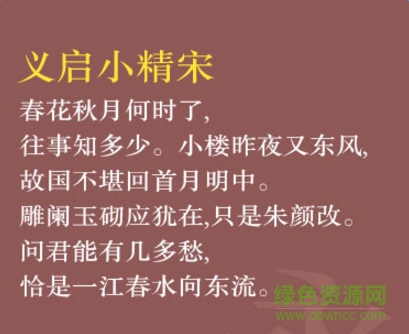
義啟小精宋字體是一款義啟類精致宋體風(fēng)格字體軟件,小精宋體融合了現(xiàn)代時尚氣息,通過圓潤的起筆與收筆,盡顯字體高端大氣,非常的耐看,感興趣的朋友歡迎來綠色資源網(wǎng)下載體驗(yàn)!
義啟小精宋的起筆和收筆處的修飾部分,更加圓融。不僅適合了小屏幕手機(jī)顯示的特性,而且注入了現(xiàn)代質(zhì)感因素。橫筆畫與豎筆畫比例更加和諧美觀;繼承了傳統(tǒng)宋體的結(jié)構(gòu)疏朗又介入了黑體的勻稱和諧,在閱讀方面不但加強(qiáng)了可訴性同時更加適應(yīng)了手機(jī)屏幕的閱讀習(xí)慣。塊面的布局更加勻稱,但即白當(dāng)黑的效果不減反增。